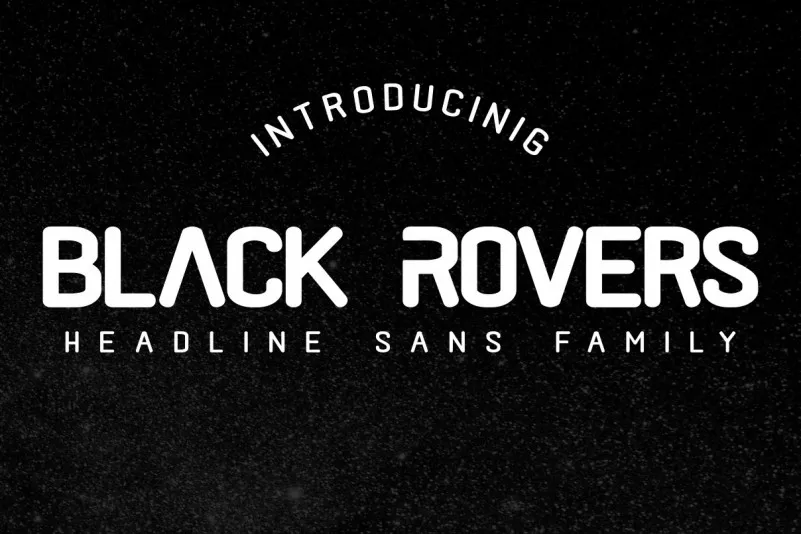
Black Rovers Sans Font
A Black Rovers Sans é uma elegante fonte sem serif com um charme moderno e marcante. Esta escolha de tipo traz consigo uma dose atraente de minimalismo, perfeitamente adaptável para qualquer projeto gráfico. Seja para adicionar um toque contemporâneo em seu logotipo ou criar um design linear e clean para sua página web, Black Rovers vai transformar o visual do seu trabalho de forma brilhante. Se você está procurando uma fonte que se destaca por ser moderna e minimalista, a Black Rovers Sans é uma ótima escolha.